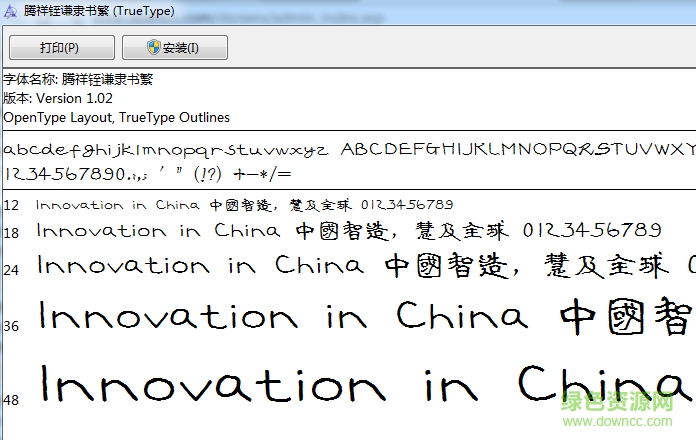
騰祥铚謙隸書繁字體是騰祥字體中一款個(gè)性繁體字體,該字體非常飄逸靈性,擁有很豐富的字體構(gòu)造,個(gè)性的字型讓人一眼難忘,有喜歡這款字體的朋友就趕快來下載使用吧!
騰祥铚謙隸書繁字體是一款繁體字體,字體呈現(xiàn)出來的效果十分優(yōu)秀,讓用戶能夠欣賞這一字體形象,有喜歡的就趕快來綠色資源網(wǎng)下載吧!